Kalligrafie ist die Kunst des schönen Schreibens und verleiht Texten eine elegante Note. Suchst du nach der perfekten Kalligrafie-Schriftart für deine Designs? Dann bist du hier genau richtig!
Kalligrafie-Schriftarten, die du kennen solltest
Kalligrafie verleiht Texten Eleganz sowie eine persönliche Note. Moderne Schriftarten ahmen die typischen dicken Abwärts- und dünnen Aufwärtsstriche nach, um diesen kunstvollen Stil nachzubilden. Die Foto-App PhotoDirector bietet eine große Auswahl an Kalligrafie-Schriftarten, die du direkt in der App nutzen kannst, um deine Bilder kreativ zu beschriften und zu gestalten. Im Folgenden stellen wir dir acht hochwertige Kalligrafie-Schriftarten vor.
1. Dancing Script
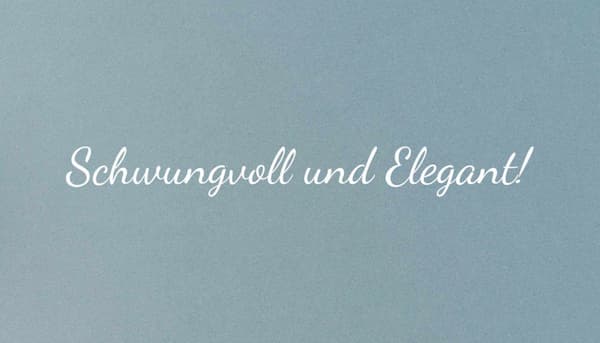
"Dancing Script" ist eine elegante Kalligrafie-Schriftart im Retro-Stil der 1950er-Jahre mit schwungvollen Buchstaben. Sie strahlt Lebensfreude aus und wirkt alles andere als langweilig. Perfekt geeignet ist sie für informelle Einladungen, Branding und kreative Designs.
2. Beth Ellen
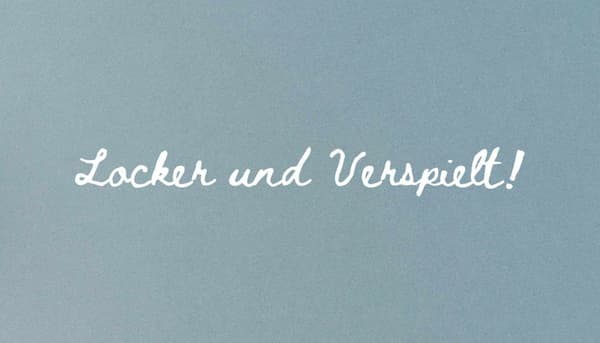
"Beth Ellen" ist eine sehr schöne Handschrift, benannt nach Beth Ellen Jelinski, die 2017 an Krebs verstorben ist. Ihr Sohn bat sie, das Alphabet aufzuschreiben, um ihre Handschrift in eine Schriftart umzuwandeln. Diese zarte Kalligrafie ist ideal für persönliche Notizen und Tagebücher.
3. Italianno
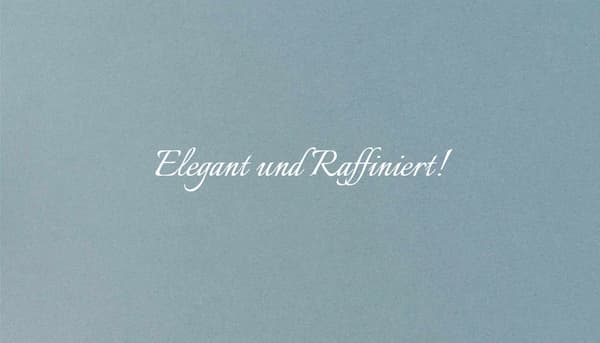
"Italianno" ist eine stilvolle Kalligrafie-Schriftart, die sich durch ihre klassische Art sowie saubere und klare Verbindungen auszeichnet. Sie ist ideal für Einladungen, Hochzeitsdesigns und Verpackungen.
4. Cookie
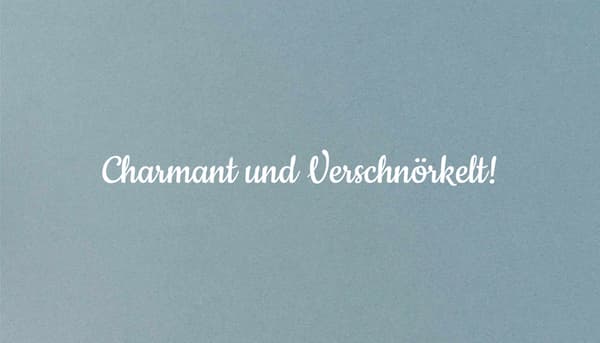
"Cookie" ist eine Schriftart, die auf Pinsel-Kalligrafie basiert. Sie erinnert an Anzeigen und Poster aus den 1950er-Jahren. Perfekt für Branding oder Überschriften im Retro-Stil.
5. Niconne
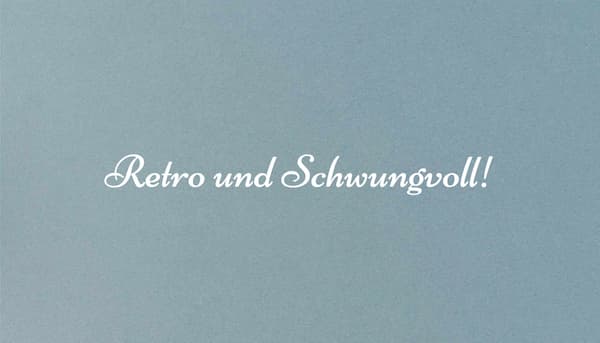
"Niconne" ist eine elegante, kursive Kalligrafie-Schriftart im Vintage-Stil. Sie zeichnet sich durch lange Oberlängen und schwungvolle Linien aus. Diese Schriftart eignet sich perfekt für Branding, Überschriften und stilvolle Designs mit einer persönlichen Note.
6. Parisienne
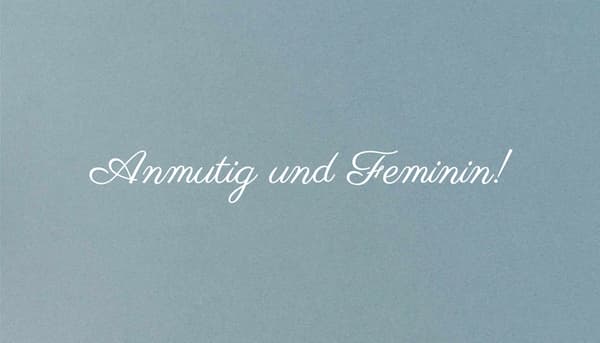
"Parisienne" ist eine moderne, fließende Kalligrafie-Schriftart, die sich durch weiche Linien und elegante Kurven im Pariser Stil auszeichnet. Sie eignet sich besonders für Hochzeitseinladungen und romantische Inhalte.
7. Sofia
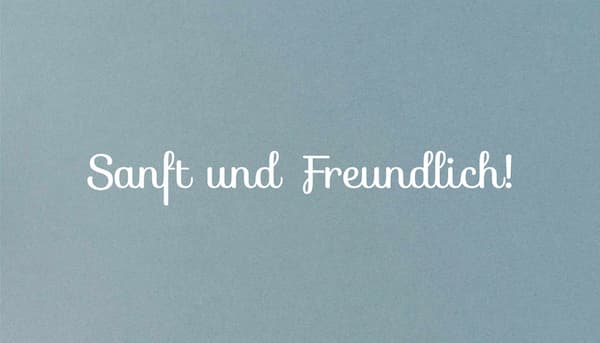
"Sofia" ist eine vielseitige und freundliche Kalligrafie-Schriftart mit einigen unkonventionellen Ligaturen. Sie eignet sich hervorragend für Blog-Überschriften, Social-Media-Posts und Kinderbücher.
8. La Belle Aurore
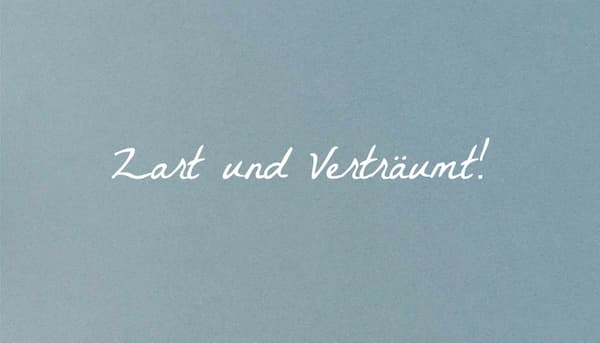
"La Belle Aurore" ist eine romantische Kalligrafie-Schriftart mit nostalgischem Charme. Die verspielten Schnörkel erinnern an eine bittersüße Handschrift. Sie eignet sich für Liebesbriefe, Tagebücher und Vintage-Designs.
Die schönste Schriftart hängt vom Stil und Verwendungszweck ab. Elegante Schriften wie Italianno wirken klassisch und stilvoll, während verspielte Schriftarten wie Beth Ellen eine lockere und persönliche Note verleihen.
Eine kalligrafische Schriftart ahmt die Kunst der schönen Handschrift nach. Sie zeichnet sich durch elegante Linien, schwungvolle Kurven und oft variierende Strichstärken aus.